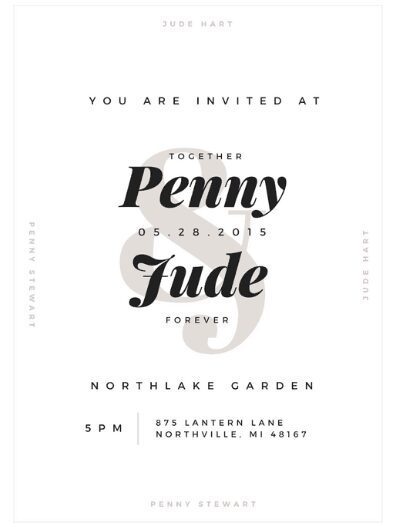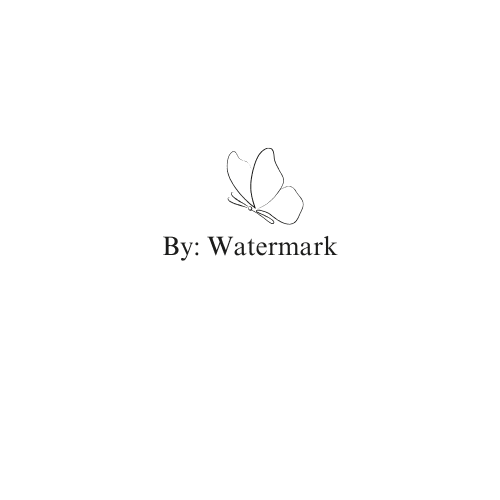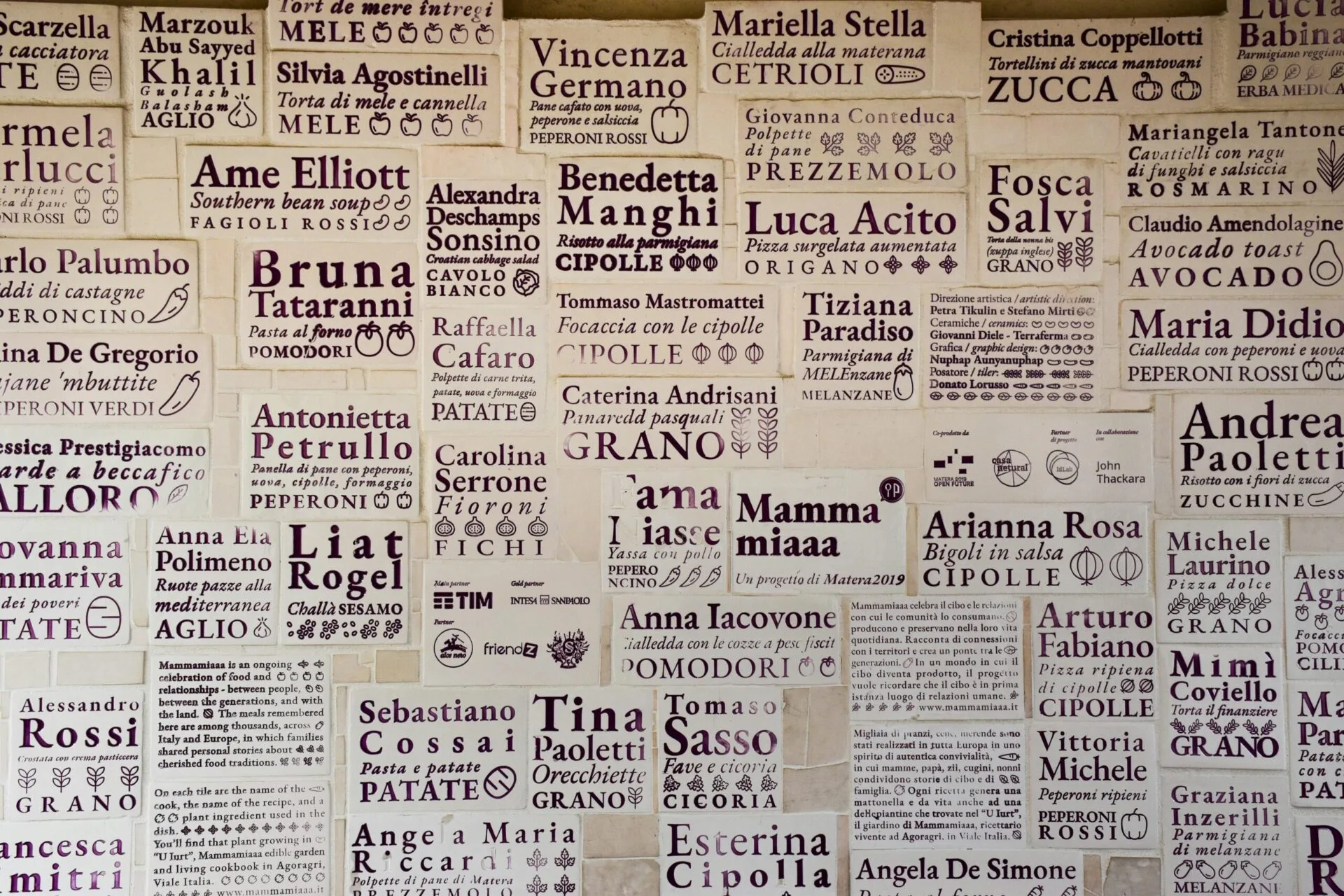
Font Bagus Untuk Nama
Font Bagus Untuk Nama. Pernahkah Anda merasa bingung memilih font yang tepat untuk menampilkan nama di sebuah desain? Entah itu untuk watermark, kartu nama, atau logo personal, pemilihan font bisa sangat memengaruhi kesan visual yang ditampilkan.
Studi menyatakan bahwa tipografi yang sesuai dapat meningkatkan daya tarik desain secara signifikan. Tak heran jika banyak orang kini lebih selektif dalam menentukan font, terutama untuk nama yang merepresentasikan identitas diri.
Berikut MinTiv akan berikan rekomendasi font bagus untuk nama.
Pentingnya Pemilihan Font untuk Nama
Pemilihan font untuk nama bukan sekadar soal estetika, font yang digunakan dapat mencerminkan kepribadian, tujuan, dan konteks dari nama tersebut. Bayangkan Anda mendesain undangan pernikahan, namun memilih font yang kaku dan menyerupai laporan akademis. Tentu kesannya jadi kurang hangat, bukan?
Contoh lainnya ketika Anda membuat logo bisnis kuliner dan memakai font terlalu dekoratif, hal ini justru bisa mengganggu keterbacaan dan membuat calon pelanggan kesulitan mengenali nama brand Anda. Itulah mengapa penting memilih font bagus untuk nama yang sesuai dengan pesan dan karakter yang ingin Anda tampilkan.
Rekomendasi Font Bagus untuk Nama
Berikut adalah beberapa rekomendasi pilihan font bagus untuk nama.
1. Times New Roman
Font Bagus Untuk Nama times new roman
Times New Roman bisa dibilang salah satu font bagus untuk nama yang bersifat formal dan klasik. Meski terlihat sederhana, font ini tetap efektif digunakan sebagai elemen teks pendukung. Misalnya untuk melengkapi nama utama yang ditulis dengan font yang lebih mencolok.
2. Trajan Pro
Font Bagus Untuk Nama trajan pro
Trajan Pro juga bagus untuk kesan elegan, tegas, dan berwibawa. Terinspirasi dari prasasti Romawi kuno, font ini sering digunakan untuk menciptakan tampilan yang klasik namun tetap kuat secara visual. Cocok untuk nama yang ingin menonjolkan otoritas, seperti dalam konteks hukum, formal, atau profesional.
3. Helvetica
Font Bagus Untuk Nama Helvetica - Wikipedia bahasa Indonesia, ensiklopedia bebas
Font ini termasuk salah satu font bagus untuk nama karena tampilannya yang simpel namun tetap jelas terbaca. Desainnya yang minimalis memberikan kesan bersih dan profesional, menjadikan Helvetica pilihan bagus untuk font nama yang ingin terlihat modern tanpa kehilangan kejelasan.
4. Black Caviar
Font Bagus Untuk Nama black caviar
Jika Anda ingin menampilkan kesan kreatif dan personal, Black Caviar bisa menjadi salah satu font bagus untuk nama. Gaya script nya yang menyerupai tulisan tangan memberi sentuhan humanis dan natural, seolah-olah nama Anda benar-benar ditulis secara manual.
Font ini juga fleksibel karena memiliki berbagai variasi dan cocok dipadukan dengan font serif maupun sans-serif untuk menciptakan tampilan yang harmonis.
5. Arial
Font Bagus Untuk Nama Arial ada dimana-mana
Arial memiliki tampilan yang bersih, tajam, dan mudah dibaca. Dirancang pada tahun 1982 oleh dua desainer ternama, Patricia Saunders dan Robin Nicholas, font ini merupakan turunan dari Helvetica dan dikenal karena kesederhanaannya yang fungsional.
Kualitas inilah yang membuat Arial tetap relevan untuk berbagai kebutuhan penulisan nama, baik formal maupun kasual.
6. Playfair Display
Playfair Display
Playfair Display termasuk font bagus untuk nama karena menggabungkan gaya serif yang minimalis dengan sentuhan elegan. Font ini sangat cocok untuk nama yang ingin tampil profesional, klasik, atau formal, tanpa terlihat kaku.
Tampilan hurufnya yang seimbang menjadikannya pilihan ideal untuk menciptakan kesan mewah namun tetap mudah dibaca.
7. Solomon
Font Bagus Untuk Nama solomon
Solomon menjadi pilihan bagus untuk tampilan font yang bergaya dan berkelas. Dengan desain serif yang minimalis namun tetap mewah, font ini mampu memberikan kesan elegan pada nama Anda.
Ditambah dengan variasi bobot huruf yang beragam, Solomon sangat cocok untuk kebutuhan branding di dunia mode, kecantikan, atau industri kreatif lainnya.
8. Riviera
Font Bagus Untuk Nama riviera
Riviera juga salah satu font bagus untuk nama, terutama jika Anda ingin tampilan yang berani dan mencolok. Font ini menggunakan huruf kapital semua dengan spasi yang lebar, sehingga nama tetap mudah dibaca meskipun tampilannya sangat khas dan modern.
Karakter visualnya yang unik membuat Riviera cocok digunakan untuk nama yang ingin tampil standout dan penuh gaya.
9. Futura
Futura, Bagus untuk Logo
Futura merupakan font bagus, cocok untuk tampilan modern dan bersih. Dirancang sejak tahun 1927, font ini mengusung gaya sans serif dengan bentuk geometris yang terinspirasi dari lingkaran.